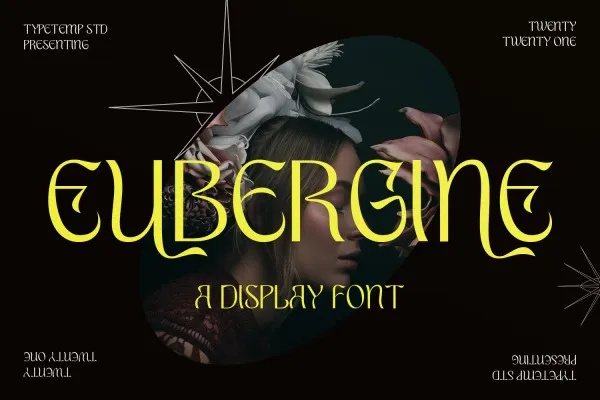
EUBERGINE Font – Fonte Grátis
EUBERGINE Font
A EUBERGINE Font é uma escolha ideal para designers que buscam imprimir estilo em seus projetos visuais. Esta fonte de display sans serif foi criada pela Typetemp Studio, oferecendo um novo olhar minimalista e versátil. Suas características incluem a facilidade de acesso à seleção extensa de alternativas de letras e ligaturas do OpenType, permitindo aos designers selecionarem as opções preferidas para criar uma fonte de display única. Ideal para projetos editoriais, identidades visuais, rótulos de marca para roupas, embalagens de produtos ou capas de revistas, a EUBERGINE é também uma excelente escolha como um overlay de texto para qualquer imagem de fundo. Esta fonte traz uma graça inovadora e um toque hipnótico ao design, tornando-a perfeita para diversos aplicativos gráficos.